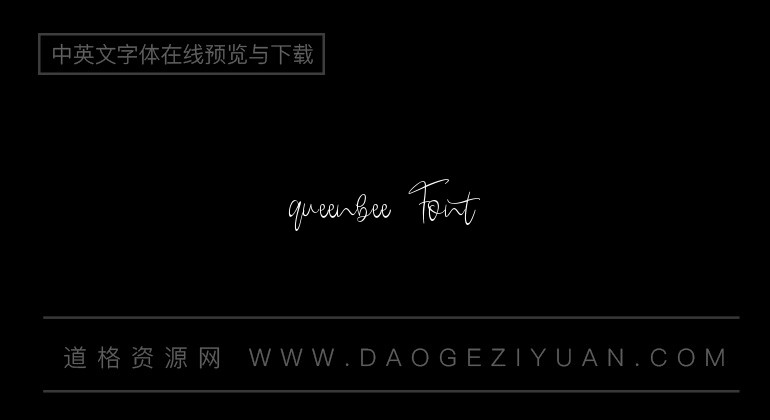
queenbee Font
Queenbee Font 是一种现代风格的手写字体,具有明显的斜体,流畅的曲线和独特的笔画。这种字体可以用于设计卡片、海报、标志和其他创意项目,特别适用于女性市场和时尚品牌。 Queenbee Font包含大写字母、小写字母、数字和基本的标点符号,支持英文和西欧语言。该字体为TTF格式,可以在任何支持该格式的设计软件中使用。
queenbee Font是一款非常不错的手写艺术字体,具有很好的视觉感,适合于文化类的宣传设计、商业类品牌的广告和产品包装设计以及个性化文字排版等较多场景。